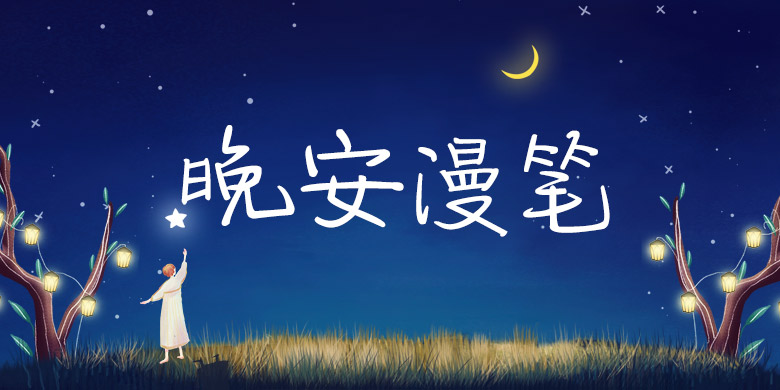
方正手迹书法字体-晚安漫笔简体方正手迹-晚安漫笔品牌: 方正手迹,方正字体下载,方正字库,方正字体, 设计师:谢劼, 发行时间:2019, 字库编码:大陆简体(GB2312-80), 分类:常规书写·硬笔,标签:力量,手写,方正手迹,2019新字体,字体介绍:方正字迹-晚安漫笔有着硬笔书法字的特点,笔触粗放苍劲不失潇洒,个性手写的灵动和英气体现得淋漓尽致,无论是文艺主标题还是正文书写均是很养眼的。广泛适合用于文艺类的书刊、品牌广告和产品包装设计,综艺节目字幕以及社交网络的个性化用字。POP字体下载官网下载 发布日期 2019年11月17日 发布于 书法字体 上篇文章: 方正字迹-杜墨飞钢笔楷书 简FZZJ-DMFGBKSJW.TTF 下篇文章: 汉仪时光体W 发表回复 取消回复要发表评论,您必须先登录。